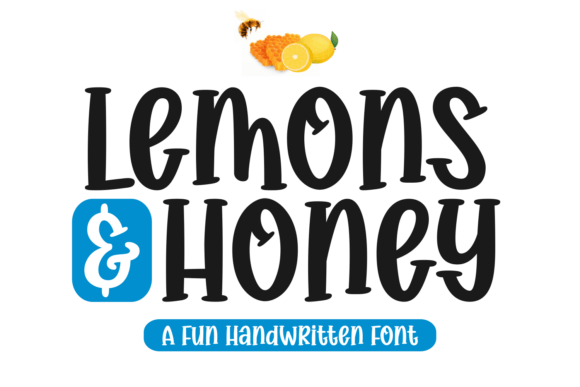
Lemons and Honey
適切なデザイン要素を見つけるのは難しい場合がありますが、Lemons and Honeyは作品を即座に引き立てる優れたコレクションを提供します。
POD(オンデマンド印刷)製品、結婚式の招待状、またはソーシャルメディアのグラフィックを作成している場合でも、Lemons and Honeyは理想的です。